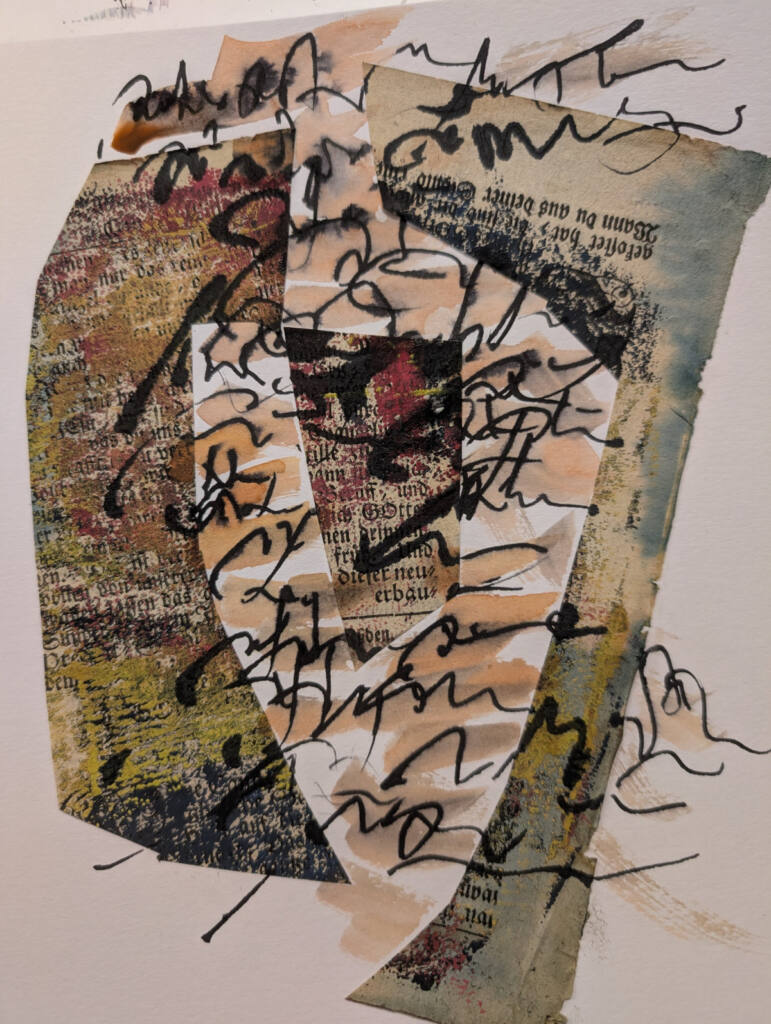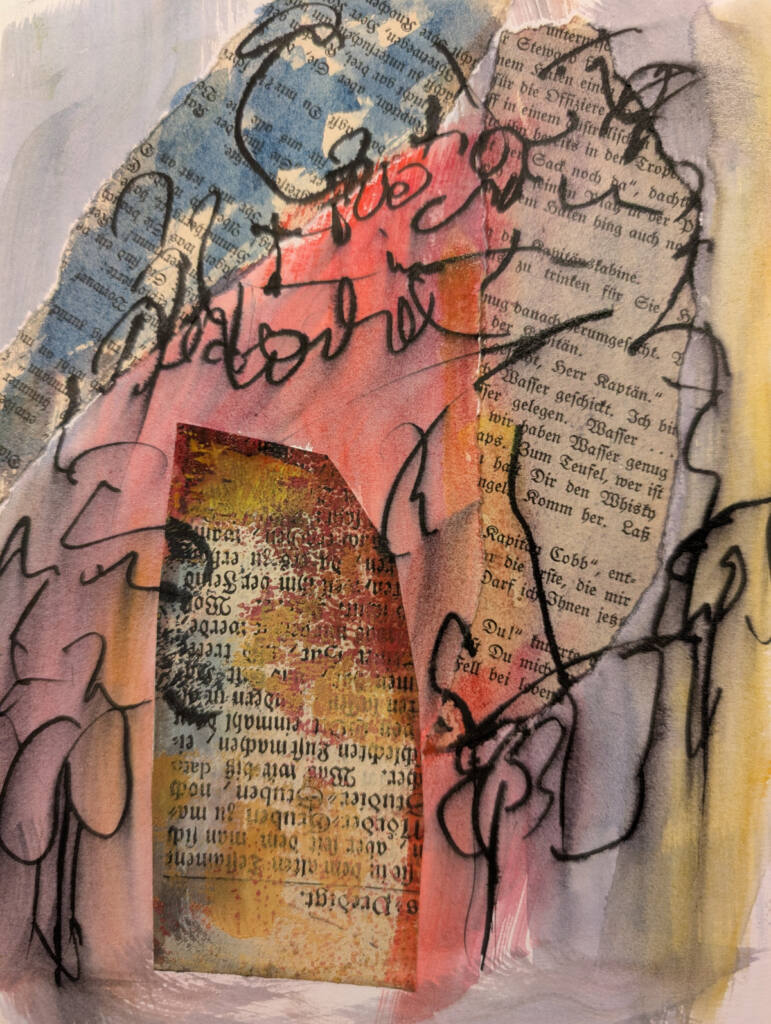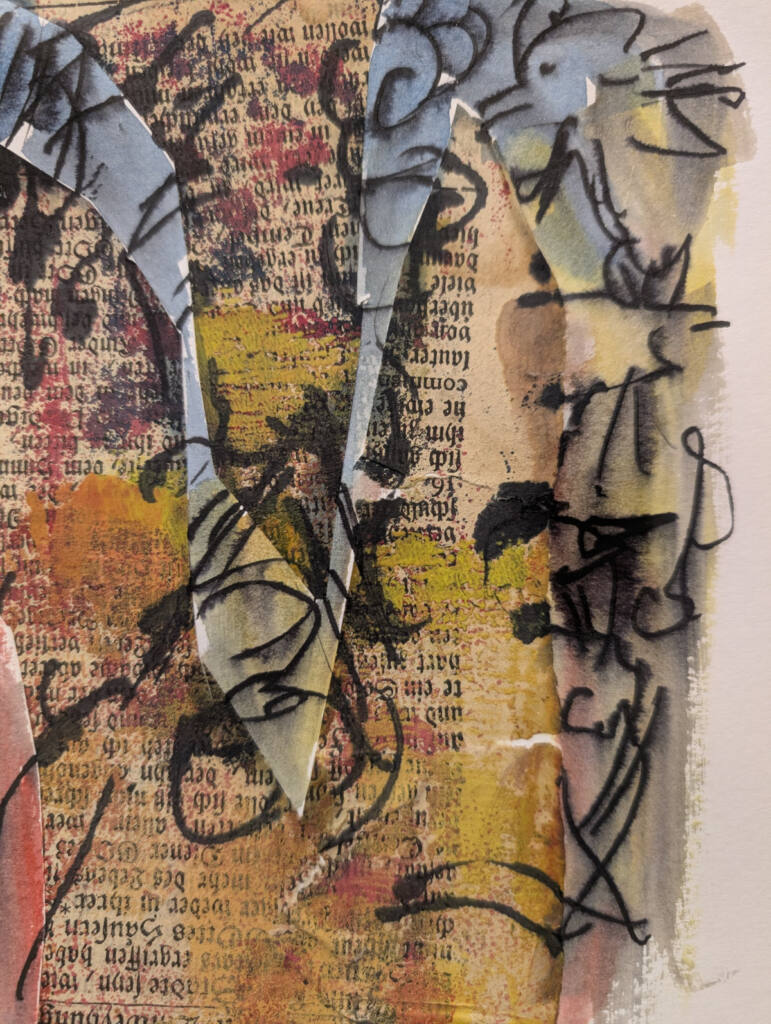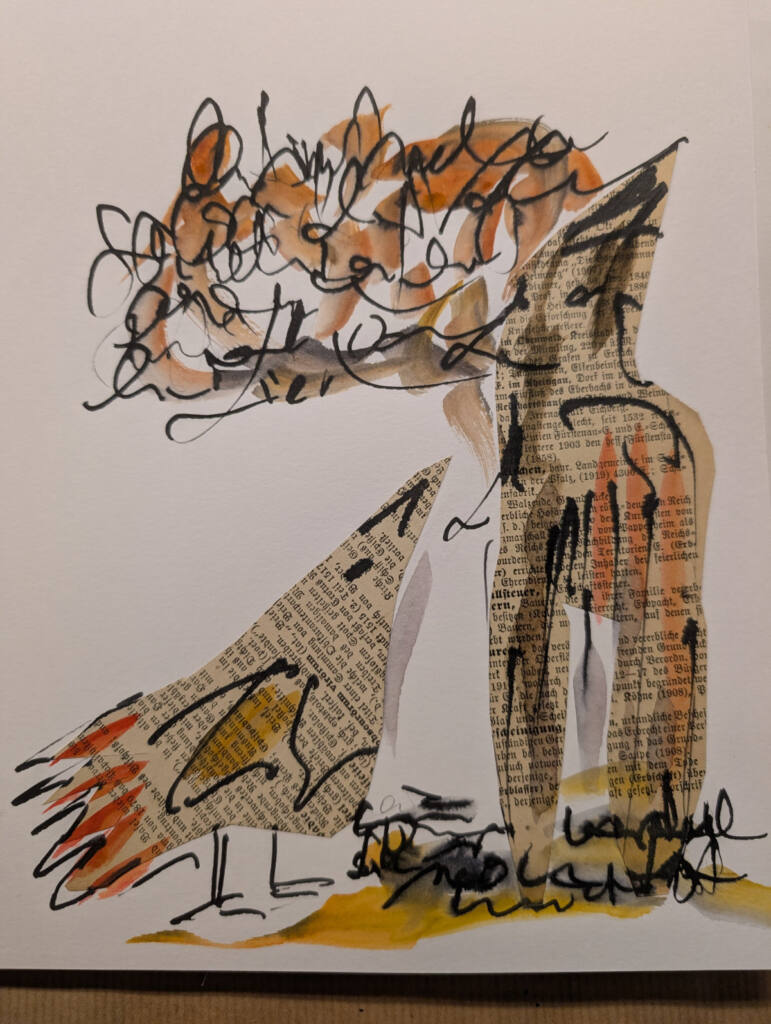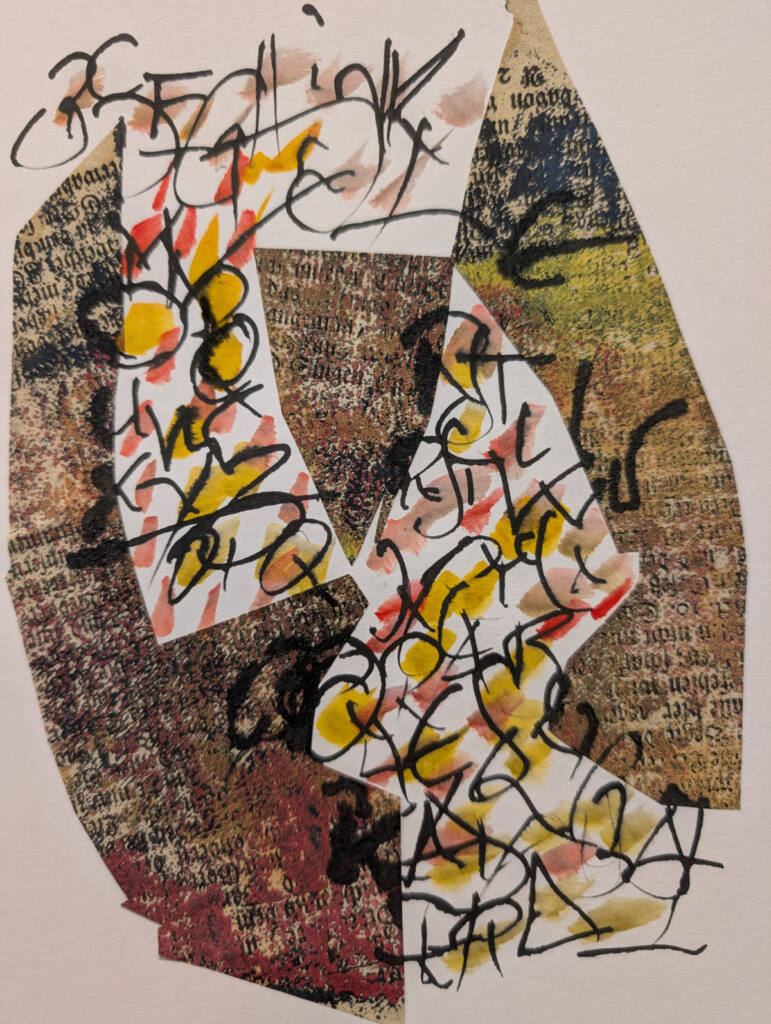
Schriftgezwitscher
Collage, Schrift und Farbe
Der Frühling geht nun in den Sommer über und das Zwitschern der Vögel lässt schon allmählich nach. Die Vogelpaare haben sich gefunden, viele gebrühtet und einige sicher Nahwuchs.
Aus der Idee des Zwitscherns ist nun die Idee für die nächsten Mittwoch-Abende entstanden. Zwitschern kann ja ganz unterschiedlich aussehen / klingen.
Gedruckte Seiten auf altem Papier, übermalt oder mit Farbe überrollt, dadurch auch ein Stück brüchig geworden, Zerrissen oder zerschnitten mit und ohne erkennbare Form, mit Farbe bearbeitet und mit lesbarer oder auch nicht lesbarer Schrit überschrieben. Die Muster zeigen Ideen dazu. Und es muss nicht unbedingt ein Vogel herauszwitschern. - Ideen entstehe und gibt es genug.
WIr arbeiten uns durch Papier und Blätter vor und fassen es dann in einem Buch voller Gezwitscher!